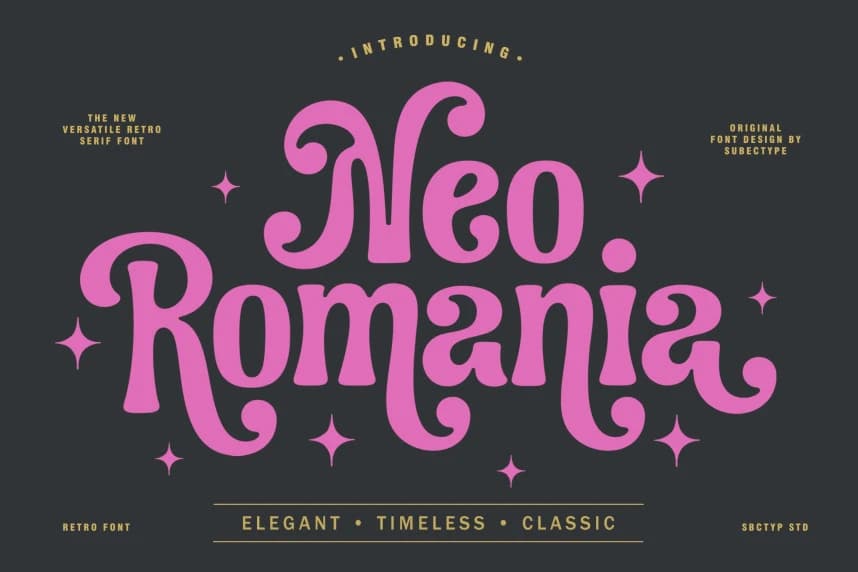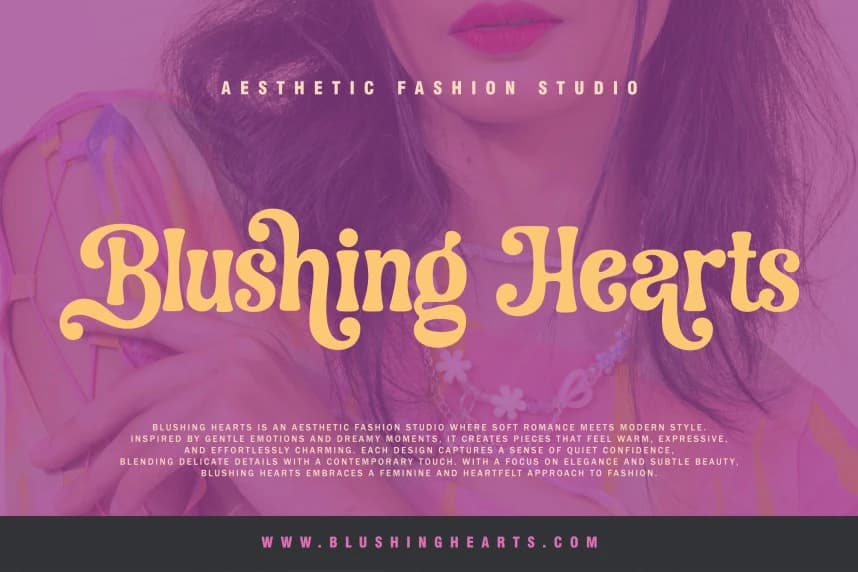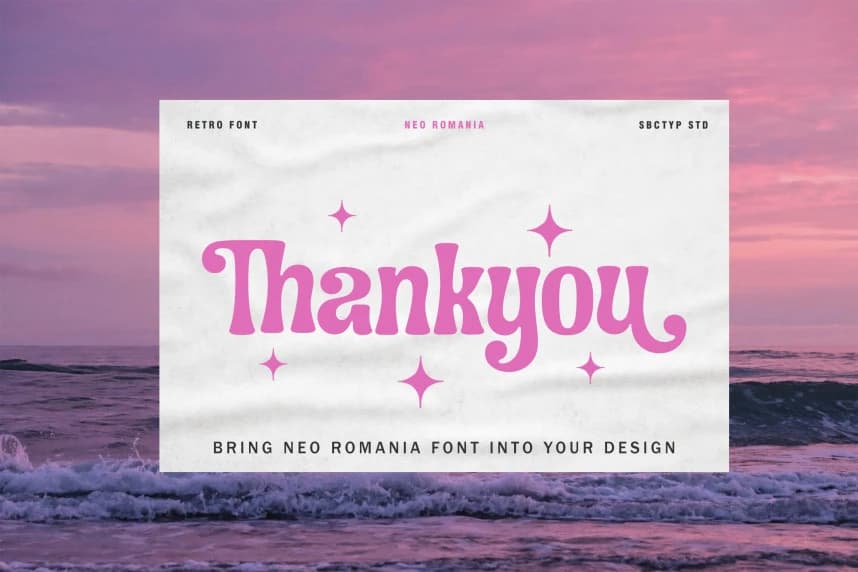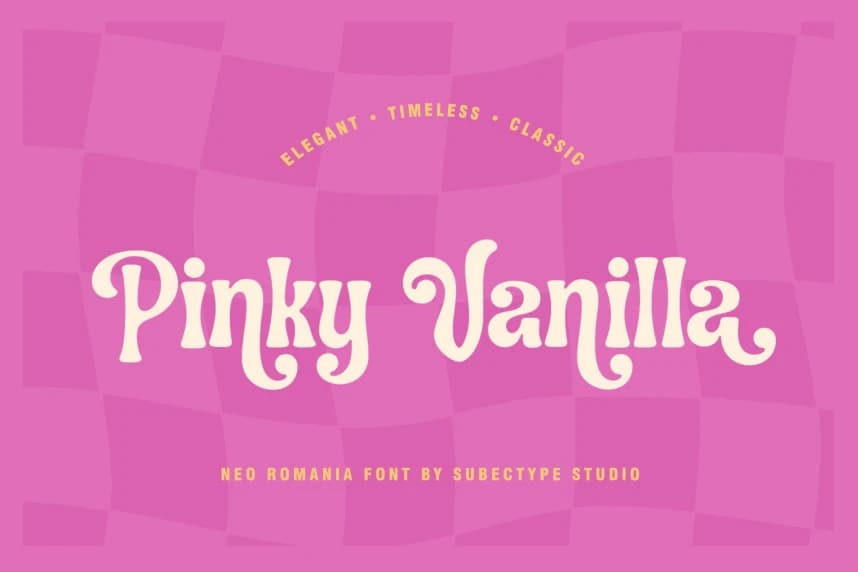
Neo Romania Font
Neo Romania Font, zarif, zamansız ve klasik bir serif fontudur; vintage çekiciliğini modern çok yönlülükle harmanlar. Retro estetiklerden ilham alan bu font, yumuşak eğriler, kalın çizgiler ve belirgin süsleme detaylarıyla herhangi bir tasarıma sofistike bir hava ve karakter katar.
Neo Romania Font zarif, zamansız ve klasik bir serif yazı tipidir; vintage cazibeyi modern esneklikle birleştirir. Retro estetiklerden ilham alan bu yazı tipi, yumuşak eğriler, kalın hatlar ve belirgin süslemeli detaylar sunar; her tasarıma sofistike ve karakter katar.
Neo Romania